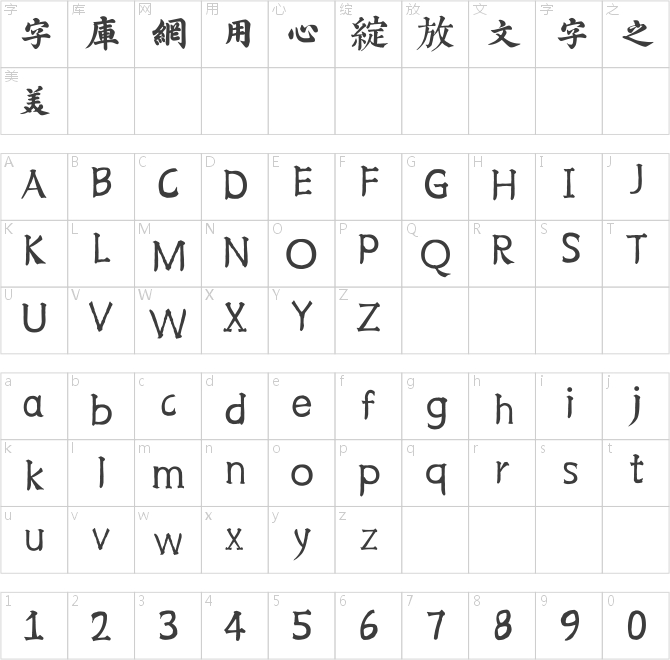
邯鄲榜書千字文字體下載邯鄲(朝)榜書千字文
注:本字庫為古籍千字文復刻書法小字庫,字符數量為1000余字,如有特殊需求,可以聯系邯鄲字庫韓紹杰為您訂制,也可以聯系本站客服為您轉答!邯鄲榜書千字文字體邯鄲(朝)榜書千字文字庫是一款讓人賞心悅目、百看不厭的中文字體,適合各類廣告和產品包裝設計應用,字體大小6.83MB,格式為ttf字體,上傳用戶是邯鄲字庫,作者/版權方為韓紹杰